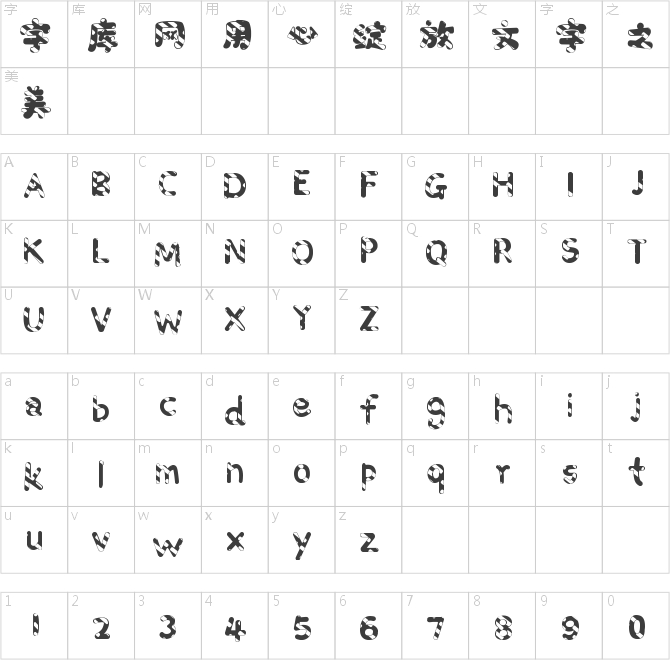
字魂158號-萌趣彩虹曲奇
字魂158號-萌趣彩虹曲奇字體zihun158hao-mengqucaihongquqi字庫是一款讓人賞心悅目、百看不厭的中文字體,適合各類廣告和產(chǎn)品包裝設(shè)計應(yīng)用,字體大小9.73MB,格式為ttf字體,上傳用戶是尚永科技,作者/版權(quán)方為字魂